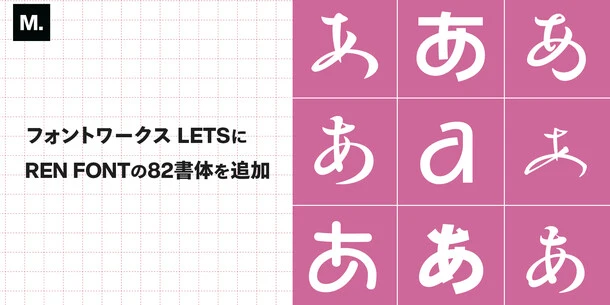
Monotype、年間定額制フォントサービス「フォントワークスLETS」にREN FONTの82書体を追加
【REN FONTのご紹介】 NPO法人日本タイポグラフィ協会主催の作品展「年鑑」のタイプフェイス部門で入選を重ね、着実に実績を積んできたREN FONT。 |
かわいらしく軽やか、そしてオールマイティな書体「和音 Pro」
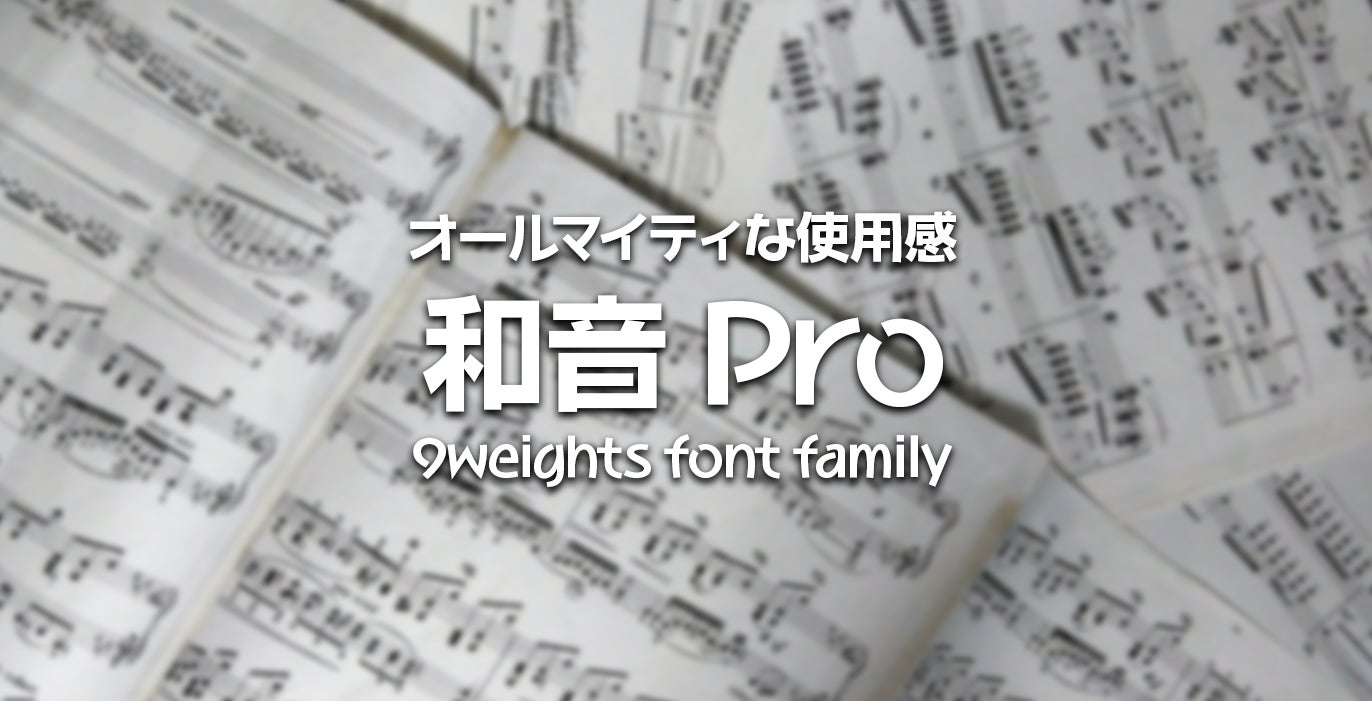
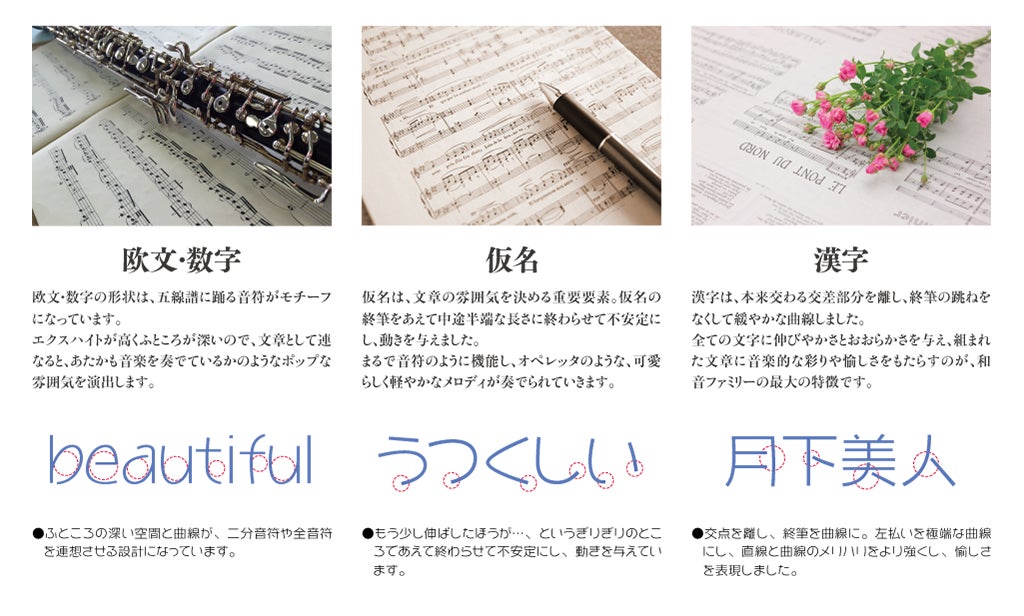
REN FONTによる「和音 Pro」のご紹介漢字、平仮名、片仮名、欧文、記号類、用途字種、数字の各字種に音楽的表現を施し設計。それぞれがもつ特徴が見事に調和する、REN FONTタイプデザイナー 金井和夫渾身の労作です。最細ウェイト「L(ライト)」から最太ウェイト「U(ウルトラ)」に至る、合計9ウェイトと多ウェイト化。本文から見出しまで幅広いニーズに応えました。まさに「和音=ハーモニー」の名にふさわしい仕上がりとなっています。ぜひ、さまざまなシーンでご利用ください。 |
清らかな水の流れのように、美しく味わい深い書体「清流かなOTF」
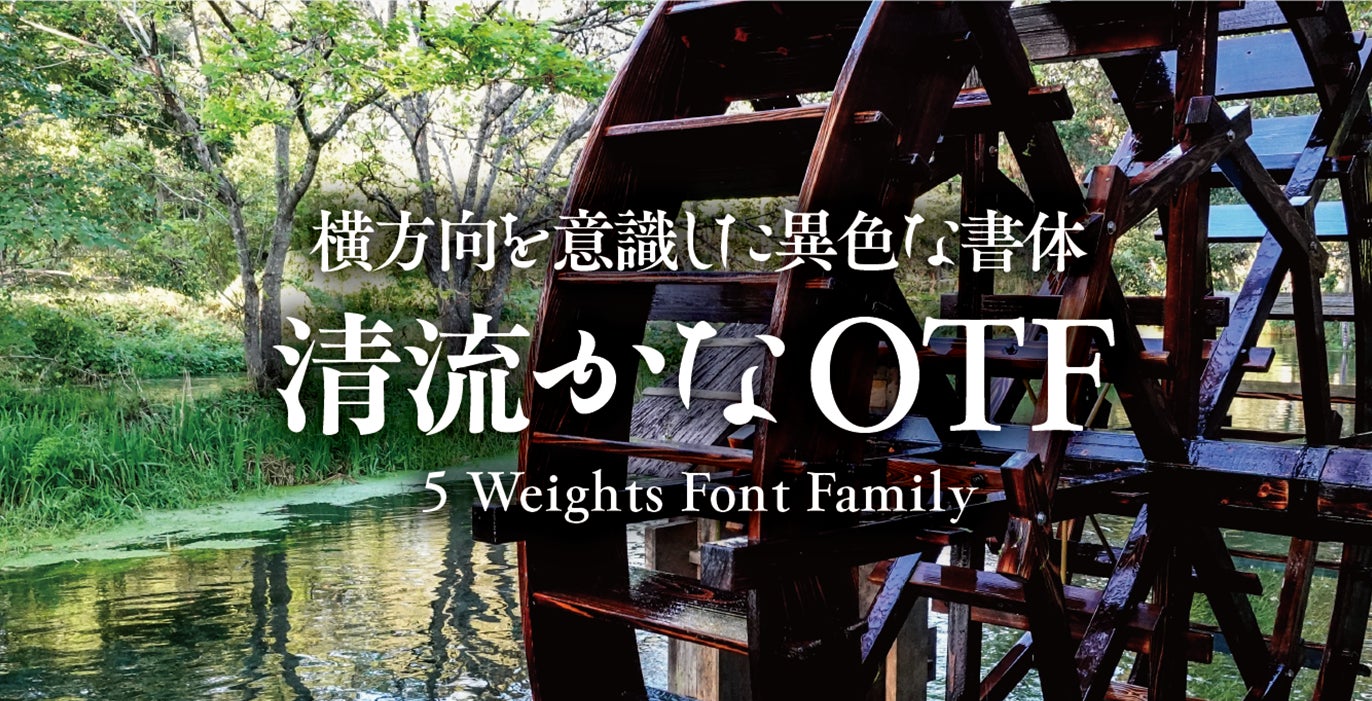
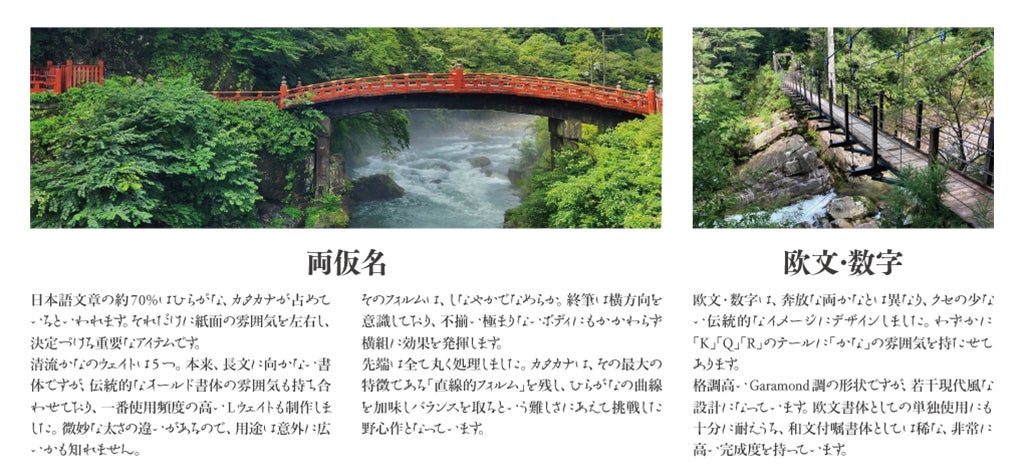
REN FONTによる「清流かなOTF」のご紹介清流かなOTFは、REN FONTタイプデザイナー 金井和夫の普段使いの手書き文字をベースとした、明朝体そして草書体の複雑なフォルムイメージを持った書体です。 |
かすかに筆文字の名残りを感じる、味わいのある丸文字「ほんまるかな」
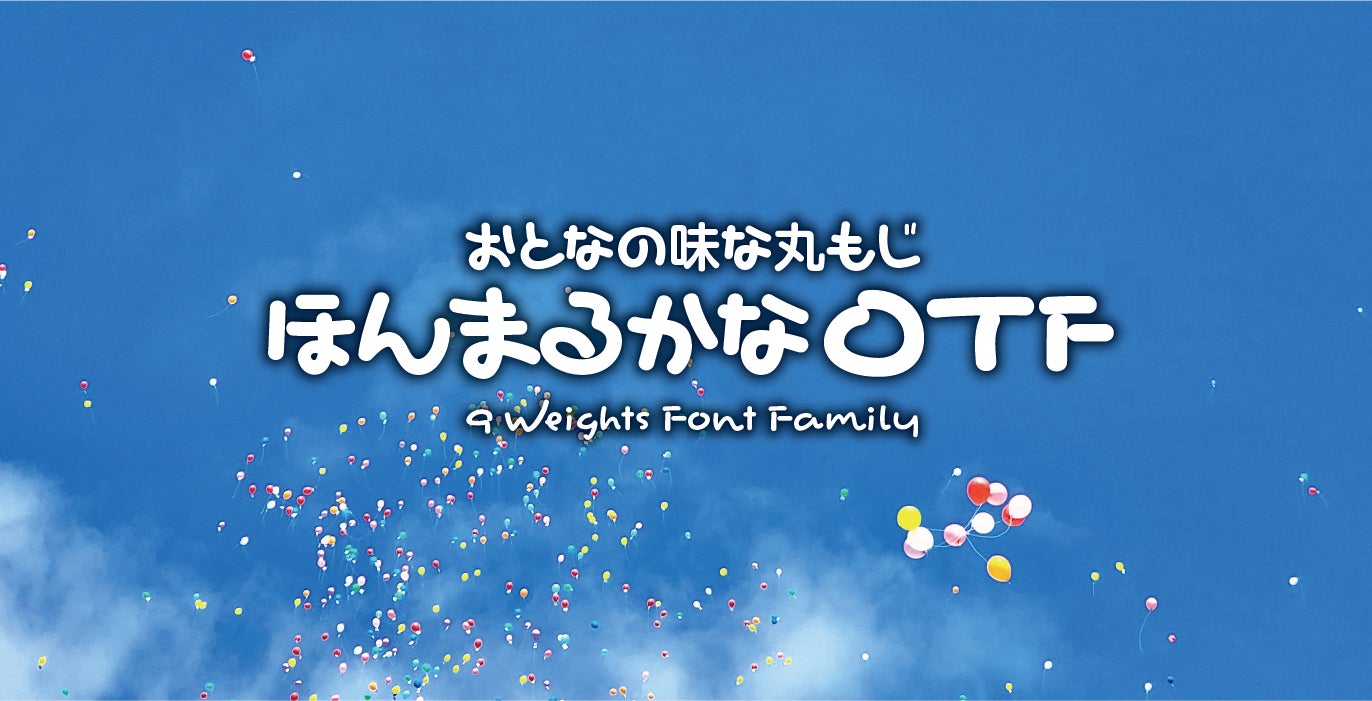
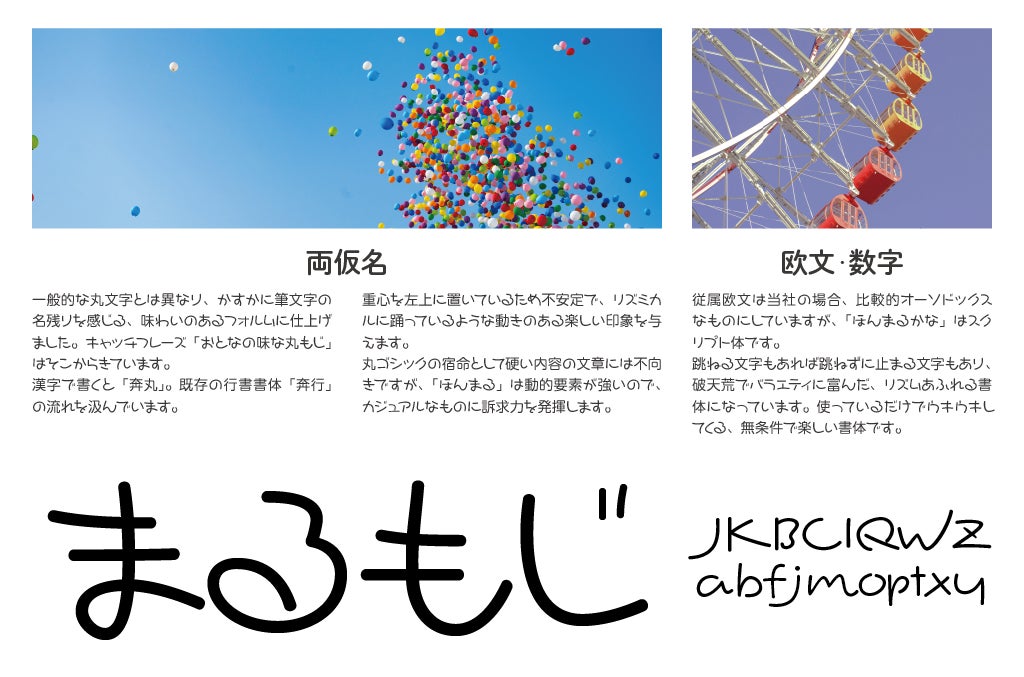
REN FONTによる「ほんまるかな」のご紹介ほんまるかなは、REN FONTタイプデザイナー 金井和夫の普段使いの手書き文字をベースとしてデザインされた書体です。わずかに筆文字の筆跡を残した、一風変わった丸文字的フォルムイメージを持っています。 |
| 和音 Pro | L / R / M / DB / B / EB / H / EH / U |
| 松葉かな Std | L |
勢蓮呉竹仮名 Classic OT | EL / L / R / M / DB / B / EB / H / U |
| 勢蓮明朝仮名 Classic OT | EL / L / R / M / DB / B / H / U |
勢蓮明朝仮名 Old OT | M |
| 靜呉竹 | UL / EL / L / R / M / DB / B / EB / H / U |
| 清明かな | R / M /B |
| ほんまるかな | EL / L / R / M / DB / B / EB / H / U |
| 余韻かな | L / R / M / DB / B |
| 靜明朝大かな | L / R / M / DB / B |
| 靜明朝小かな | L / R / M / DB / B |
| はっぴ かな | M / B / H |
| Amabile | Light / Regular / Medium / DemiBold / Bold / ExtraBold / Heavy / ExtraHeavy / Black |
| 清流かな | L / R / M / DB / B |